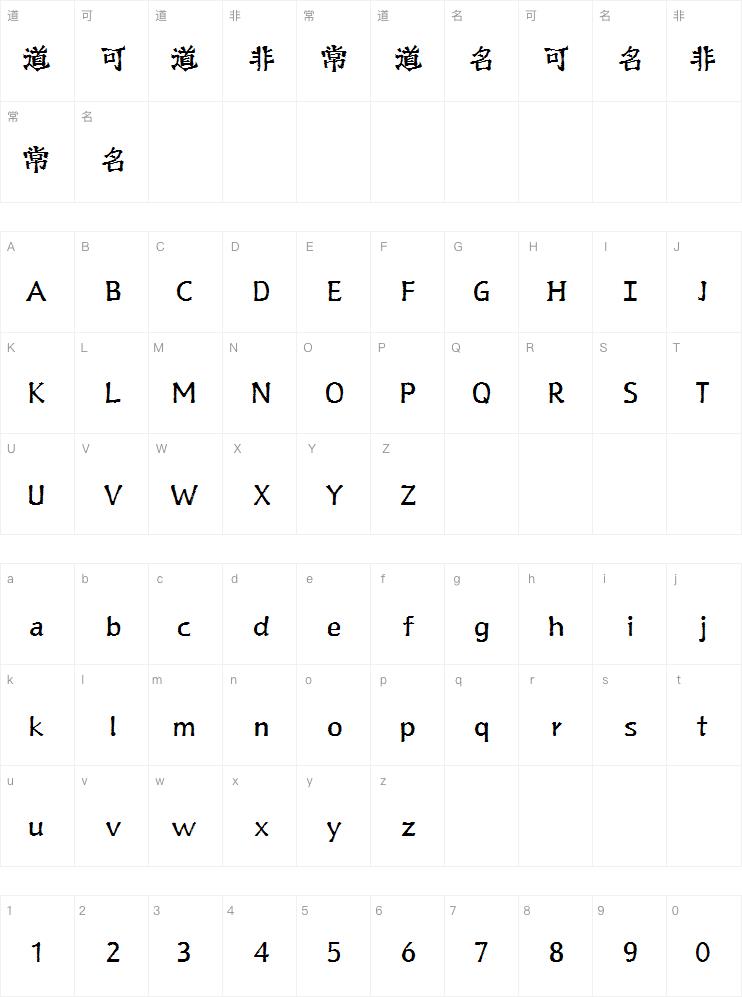
山海淘气鬼手书w
山海淘气鬼手书,是一款全新的毛笔风字体,包含汉字9169个,符号200+个。该字体运用独特的毛笔笔锋,在制作过程中融入卡通的手写方式,枯笔形成游丝飞白,从而使得该字体字形灵动多变,在灵动的同时而又极富俏皮感。在粗细的纵横间,拥有非常规的自由灵动特性。笔画的飞白效果使字体的气息更加流畅,笔画间的关系密不可分,同时也增加了字体的自由洒脱之感。这款字体古韵悠扬而不失灵动,静中有动,收放有序,适合作为标题字体应用于书籍封面、影视标题、展览广告等多种场景。